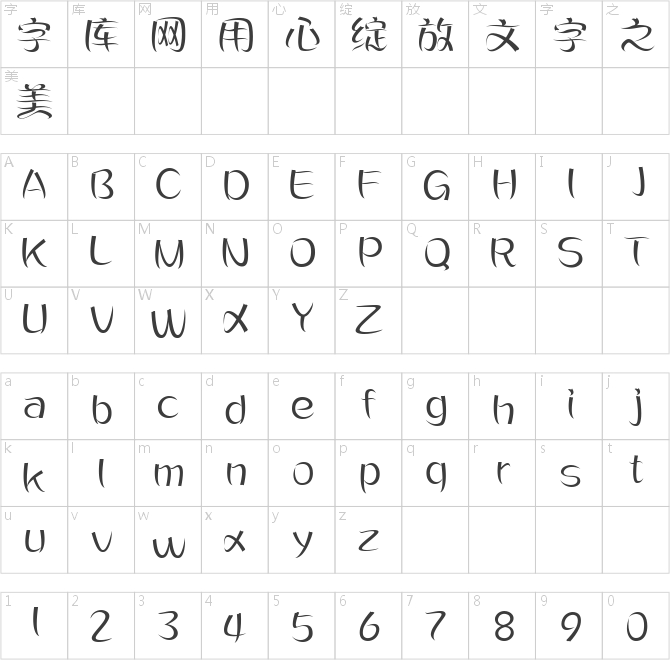
字體名稱: 絲路吠陀體
絲路吠陀體字體是一款創意藝術字體,字體靈感來源于絲帶,字形結構飄逸隨性,筆畫順暢優美,撇捺設計是連筆,有飄動的絲帶的特點
絲路吠陀體字體字庫是一款讓人賞心悅目、百看不厭的中文字體,適合各類廣告和產品包裝設計應用,字體大小12.47MB,格式為ttf字體,上傳用戶是三極字庫,作者/版權方為三極字庫